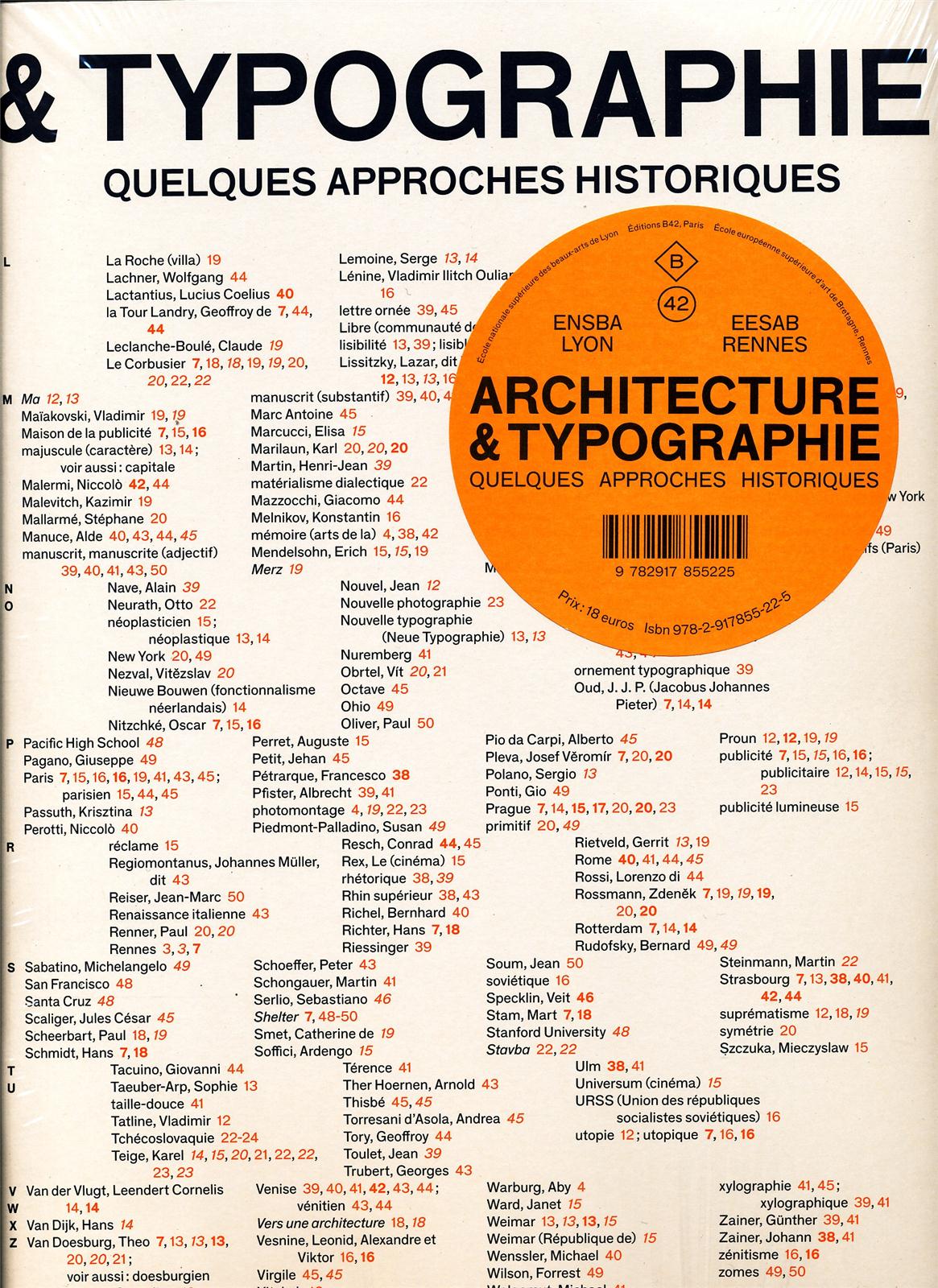
Actes du colloque de l'École des beaux-arts de Lyon et de Rennes.
Mené par trois enseignants, l'un à l'école d'art de Lyon et les deux autres à l'école d'art de Rennes, l'atelier Architecture et Typographie a réuni un groupe d'étudiants en design graphique issus des deux établissements, autour d'un projet éditorial commun.
Typographie et architecture entretiennent, dans l'espace du livre ou dans l'espace urbain, à l'échelle de la page, du monument ou de la ville, des relations étroites : modèle architectural pour la mise en forme du texte et le dessin de la lettre, ou modèle typographique pour l'épigraphie, invention et diffusion des formes architecturales par des moyens graphiques, ou encore concurrence symbolique entre l'écrit et le bâti dans la sphère publique.
Ce terrain extrêmement riche permet d'explorer différents enjeux de la pratique du design graphique en les reliant aux problématiques esthétiques, anthropologiques et politiques développées par la théorie architecturale et urbaine, renouant ainsi le lien historique entre ces deux domaines qui furent, de la Renaissance aux avant-gardes du XXe siècle, souvent considérés comme analogues, et qui donnèrent lieu parfois à des pratiques conjointes, comme les deux faces d'une même activité.
Sommaire :
Les Avant-gardes et la métropole, Sonia de Puineuf.
Les constructeurs de livres, Sonia de Puineuf
La parole est maintenant à..., Philippe Buschinger
Jiri Kroha : fragment sociologique de l'habitat, Alena Kubova-Gauché
Les lieux et les mots, Olivier Deloignon
Auto-construire son abri shelter : un récit d'expérience, Caroline Maniaque.